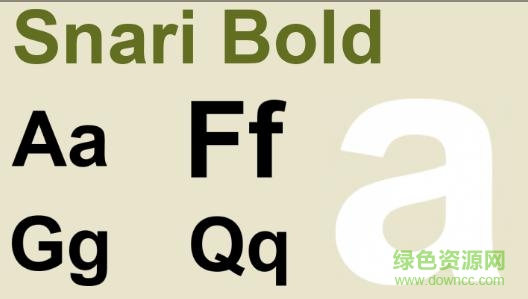
snari bold字體是一款粗粗的無襯線字體,干凈大氣,簡約時尚,可適用于報紙包裝、ppt排版、宣傳、印刷等眾多領(lǐng)域,需要的小伙伴快來下載吧!
當(dāng)我們在大字號下面使用一個字體時候(比如說一張海報),一切都被放大。所有設(shè)計上的細節(jié)都變得很明顯,同樣明顯的還有它的瑕疵。很多字體的繪制其實是很糟糕的。